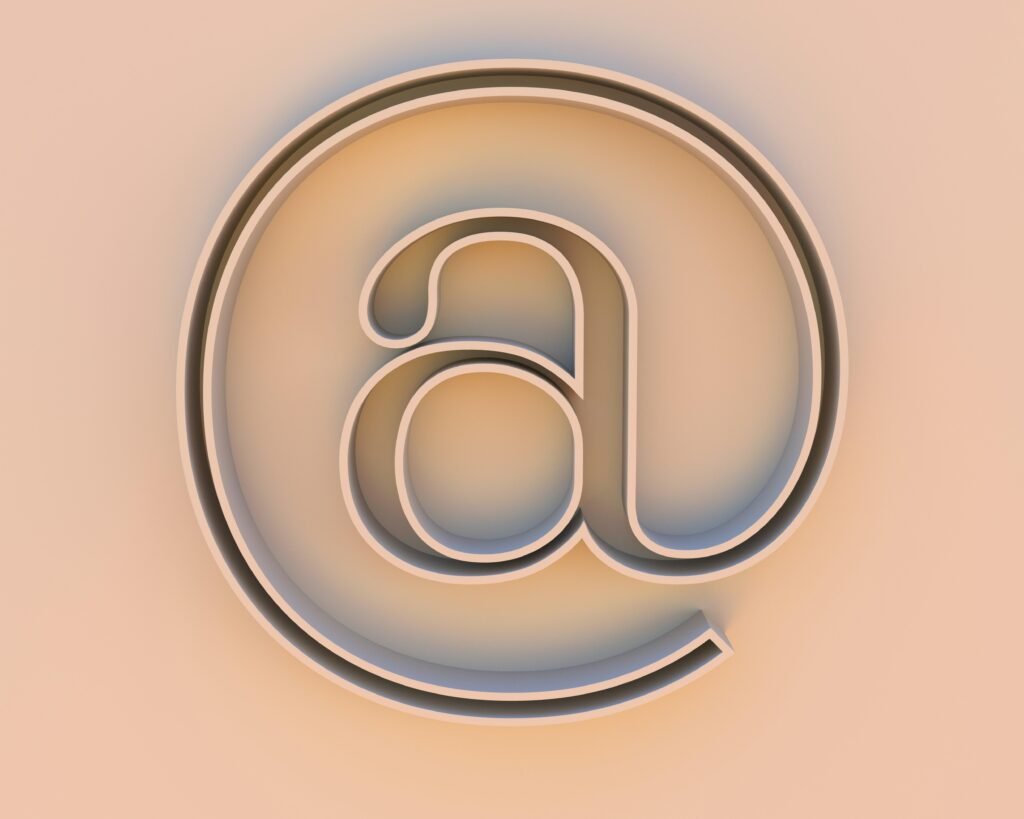
Ein großes @-Symbol in 3D-Optik steht auf einem beige-farbigen Hintergrund, neutral beleuchtet und zentriert dargestellt.
Verschiedene Schriftarten clever für Websites einsetzen
Verschiedene Schriftarten clever für Websites einsetzen: Mehr als nur hübsch
Du denkst, Schriftarten sind nur Deko für deine Website? Dann hast du wohl das Memo verpasst, dass Fonts längst ein entscheidender Faktor für User Experience und Conversion Rates sind. In diesem Artikel erfährst du, wie du mit der richtigen Auswahl und Kombination von Schriftarten nicht nur das Design aufwertest, sondern auch die Performance und Lesbarkeit deiner Seite optimierst. Spoiler: Es wird technisch, es wird tief – und es wird dir die Augen öffnen.
• Wie Schriftarten die User Experience und die Conversion Rate beeinflussen
• Die wichtigsten technischen Begriffe rund um Webfonts
• Warum die Ladezeit deiner Schriftarten über Erfolg oder Misserfolg entscheidet
• Variable Fonts: Die Zukunft der Webtypografie
• Wie du Schriftarten für maximale Performance optimierst
• Warum Google Fonts nicht immer die beste Wahl sind
• Schritt-für-Schritt-Anleitung zur Implementierung von Webfonts
• Tools und Ressourcen für die Auswahl und Optimierung von Schriftarten
• Was viele Webdesigner nicht wissen (und warum das ein Problem ist)
• Fazit: Warum du Schriftarten nicht länger ignorieren solltest
Wenn du glaubst, dass Schriftarten nur ein hübsches Beiwerk sind, das du je nach Lust und Laune austauschen kannst, dann hast du den Schuss noch nicht gehört. Denn Webtypografie ist längst kein Nice-to-have mehr, sondern ein Muss für jede ernstzunehmende Website. Und das nicht nur, weil sie visuell ansprechend sein soll, sondern weil sie direkt in die User Experience und Conversion Rates eingreift. Die richtige Auswahl und Optimierung von Schriftarten kann den Unterschied zwischen einem erfolgreichen und einem gescheiterten Online-Projekt ausmachen.
Technische Begriffe wie Webfonts, Schriftarten-Caching und Font Loading Performance sind für viele Webdesigner noch immer ein Buch mit sieben Siegeln. Dabei sind diese Faktoren entscheidend, wenn es darum geht, wie schnell und flüssig eine Website geladen wird. Und genau hier liegt der Hund begraben: Eine falsche oder schlecht optimierte Schriftart kann deine Ladezeiten in die Höhe treiben und damit sowohl deine Benutzer als auch Google verärgern.
Die Zukunft gehört den Variable Fonts, die eine nahezu unbegrenzte Vielfalt an Stilen und Gewichtungen mit sich bringen, ohne dabei die Ladezeiten negativ zu beeinflussen. Doch was bedeutet das für dich als Website-Betreiber oder Designer? Es bedeutet, dass du dich mit diesen Themen auseinandersetzen musst, wenn du im Jahr 2025 und darüber hinaus wettbewerbsfähig bleiben willst. Denn während die meisten noch mit Standard-Fonts arbeiten, kannst du mit cleverer Typografie deiner Konkurrenz den Rang ablaufen.
In diesem Artikel erfährst du nicht nur, wie du die passenden Schriftarten für deine Website auswählst, sondern auch, wie du sie so implementierst, dass sie nicht nur gut aussehen, sondern auch performen. Wir werfen einen Blick auf die besten Tools und Ressourcen, die dir bei der Auswahl und Optimierung helfen, und wir zeigen dir, warum Google Fonts nicht immer die beste Wahl sind. Am Ende wirst du wissen, wie du mit Schriftarten nicht nur dein Design, sondern auch deine Conversion Rates auf ein neues Level heben kannst.
Wie Schriftarten die User Experience und die Conversion Rate beeinflussen
Die Wahl der Schriftart ist mehr als nur eine ästhetische Entscheidung. Sie beeinflusst die Lesbarkeit, die Wahrnehmung der Marke und letztlich die Conversion Rate deiner Website. Eine gut gewählte Schriftart kann die User Experience erheblich verbessern, während eine schlechte Wahl genau das Gegenteil bewirken kann. Doch was macht eine Schriftart „gut“ oder „schlecht“?
Eine gute Schriftart zeichnet sich durch Klarheit und Lesbarkeit aus. Besonders auf Bildschirmen, die unterschiedliche Auflösungen und Betrachtungswinkel bieten, ist es wichtig, dass der Text leicht zu lesen ist. Serifenschriften wie Times New Roman gelten traditionell als gut lesbar, während serifenlose Schriften wie Arial oder Helvetica für eine moderne und klare Optik stehen.
Doch auch die emotionale Wirkung einer Schriftart sollte nicht unterschätzt werden. Schriften können Gefühle transportieren und die Wahrnehmung deiner Marke beeinflussen. Eine verspielte Schriftart kann kindlich und unprofessionell wirken, während eine klare und schlichte Schrift den Fokus auf den Inhalt lenkt und Professionalität ausstrahlt.
Die Ladezeit der Schriftart ist ein weiterer entscheidender Faktor. Langsam ladende Schriftarten können die gesamte Ladezeit deiner Website verlängern, was zu einer höheren Absprungrate führt. Und wie wir alle wissen, bedeutet eine hohe Absprungrate weniger Conversions. Daher ist es unerlässlich, Schriftarten zu wählen und zu optimieren, die schnell laden und die User Experience nicht beeinträchtigen.
Zusammengefasst: Die richtige Schriftart kann die User Experience verbessern und die Conversion Rate steigern. Die falsche Schriftart kann genau das Gegenteil bewirken. Es lohnt sich also, Zeit und Mühe in die Auswahl und Optimierung der Schriftarten zu investieren.